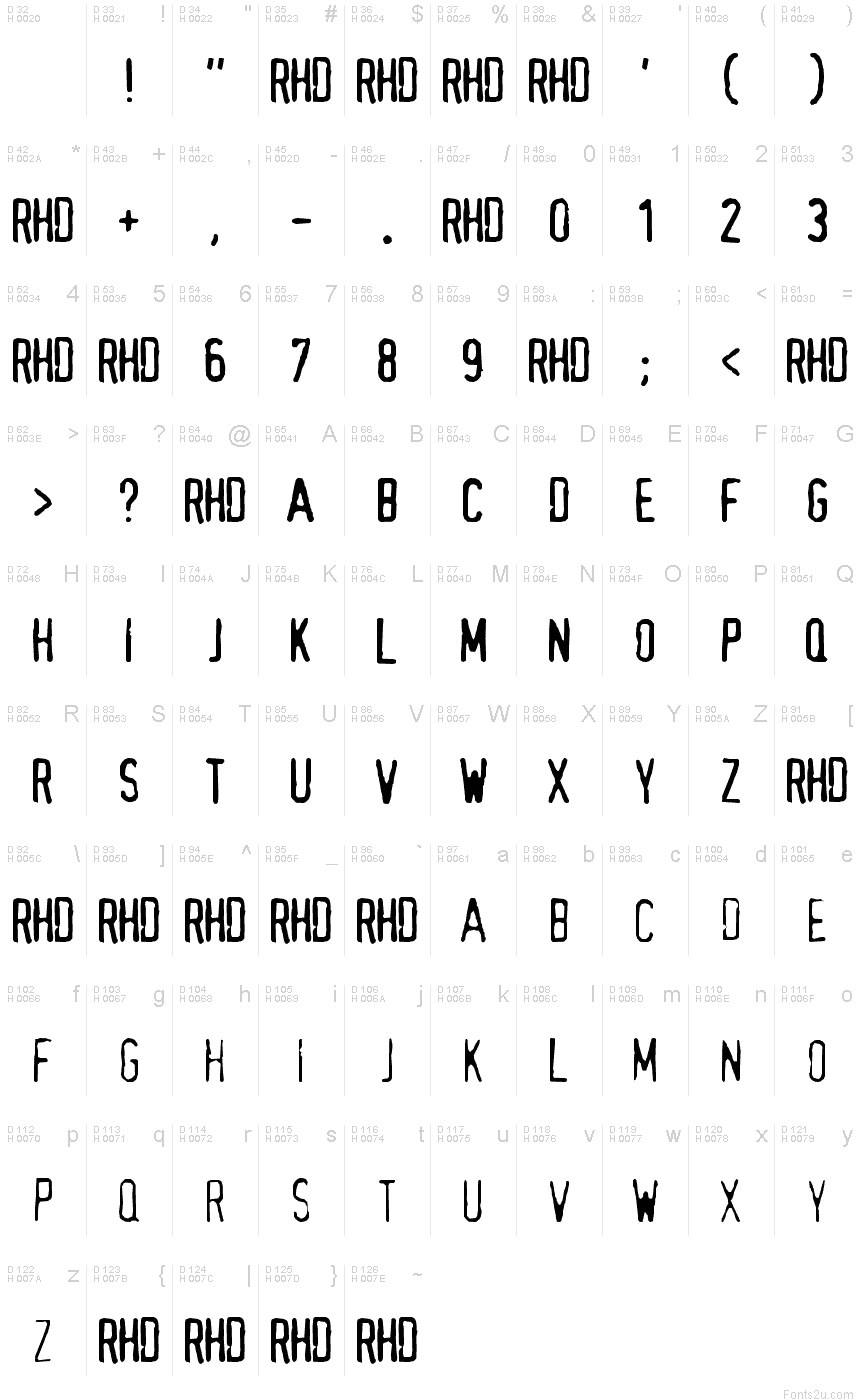
Abuse Lite è un font display di grande impatto, caratterizzato da un'estetica audace ed erosa. Progettato da RAILhead Design, questo carattere condensato emana un fascino grezzo e urbano che cattura l'attenzione.
Le forme irregolari e vissute evocano un senso di potenza e sfida, rendendolo una scelta eccellente per titoli, poster e qualsiasi progetto di design che richieda una presenza visiva forte e incisiva. La versatilità di Abuse Lite va oltre il suo aspetto drammatico: può conferire un tono audace e ribelle al branding, al packaging e persino all'impaginazione editoriale.
Il carattere unico e lo stile deciso di questo font lo rendono una scelta ideale per i designer che vogliono lasciare un segno indelebile.